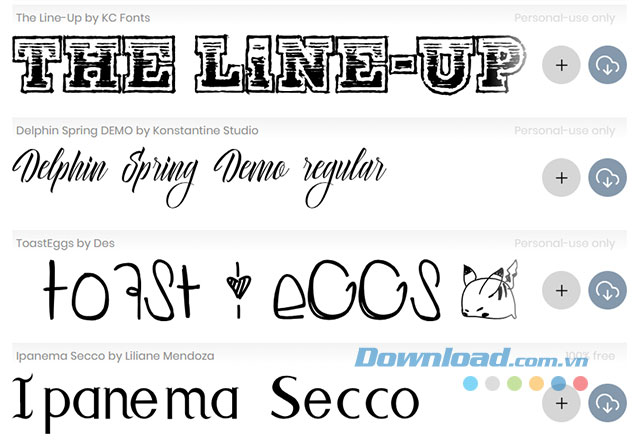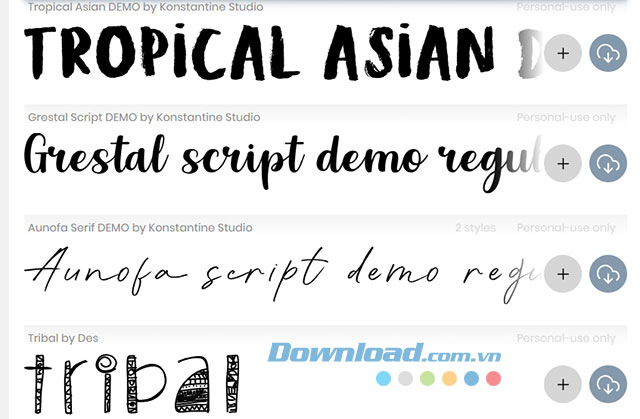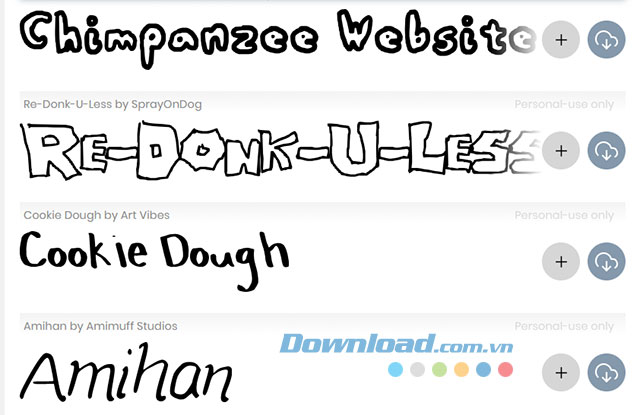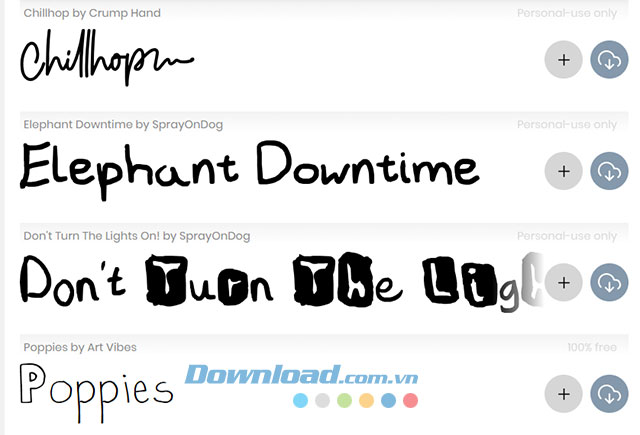
Font Chill là bộ font chữ đẹp tiếng Anh với rất nhiều mẫu chữ đặc sắc. Bộ font chữ Font Chill sẽ mang đến nguồn cảm hứng làm việc cho những ai đang sử dụng với cảm giác tươi mới, sảng khoái và vui vẻ. Tải bộ chữ Font Chill để cài đặt ngay cho máy tính của bạn và bắt đầu sáng tạo ra những mẫu thiết kế thời thượng.
Tuy nhiên từ Chill mà các bạn trẻ đang sử dụng lại có nghĩa hoàn toàn khác, nó giống như một từ lóng có nghĩa là tương đương với từ Cool hay đẹp, hay, thú vị, sảng khoái, vv. Nhìn chung Chill có ý nghĩa khá tích cực nên bộ Font Chill chắc chắn sẽ mang đến cảm hứng sáng tạo đặc biệt trong công việc và ảnh hưởng khá tốt đến giới trẻ.
Bộ Font Chill là tổng hợp 21 font chữ đẹp cho Word với phong cách Chill đúng như tên gọi, không phải là những nét chữ cứng nhắc như trong bộ Font Vni, Bộ font TCVN3 hay Bộ font Unicode mà chúng ta sẽ có những lựa chọn mới chưa từng xuất hiện trước đây mềm mại, độc đáo đảm bảo bất cứ ai cũng sẽ thích. Không chỉ vậy chúng ta có thể sử dụng Bộ Font Chill làm bộ font chữ cho Photoshop để thiết kế poster là vô cùng thích hợp.
Với những người làm công việc thiết kế đồ họa, chuyên về chỉnh sửa ảnh thì bộ Font Chill sẽ là nguồn năng lượng mới để kích thích sự sáng tạo, thử nghiệm cái mới để tạo ra những sản phẩm độc đáo, nổi bật mang đậm cá tính riêng. Tải bộ Font Chill để bắt đầu sáng tạo ra những mẫu thiết kế riêng theo cách của bạn.